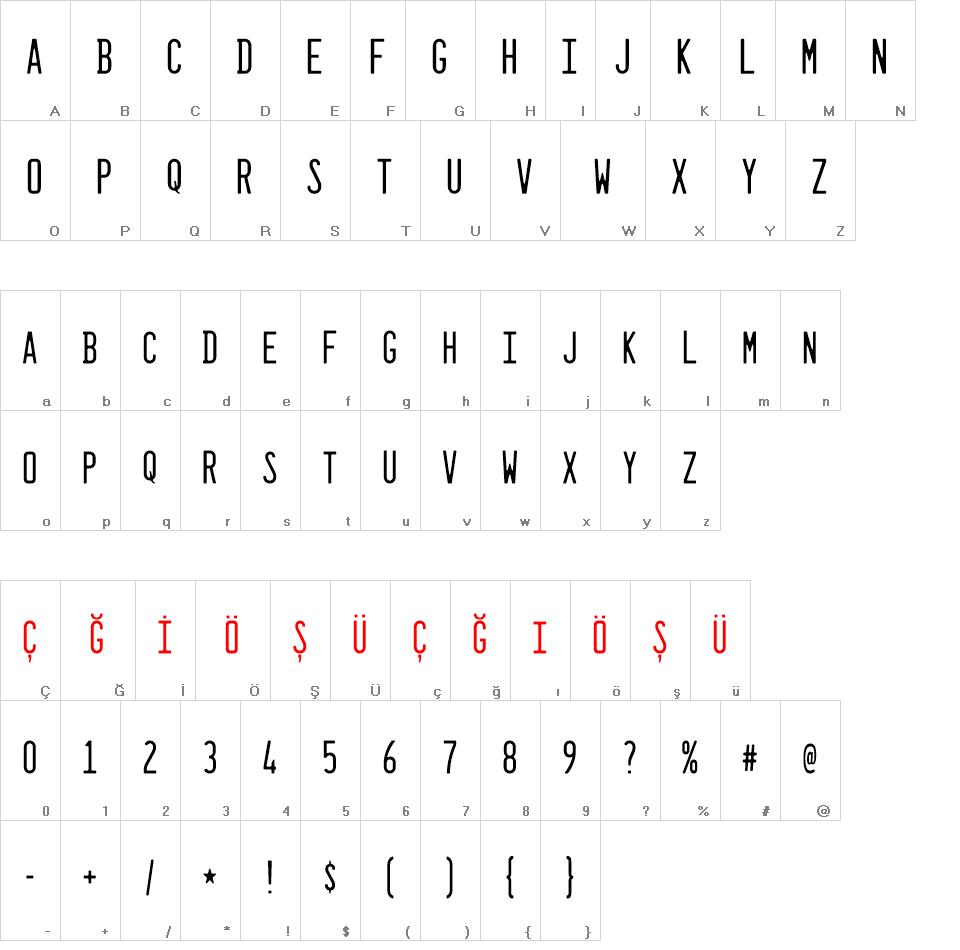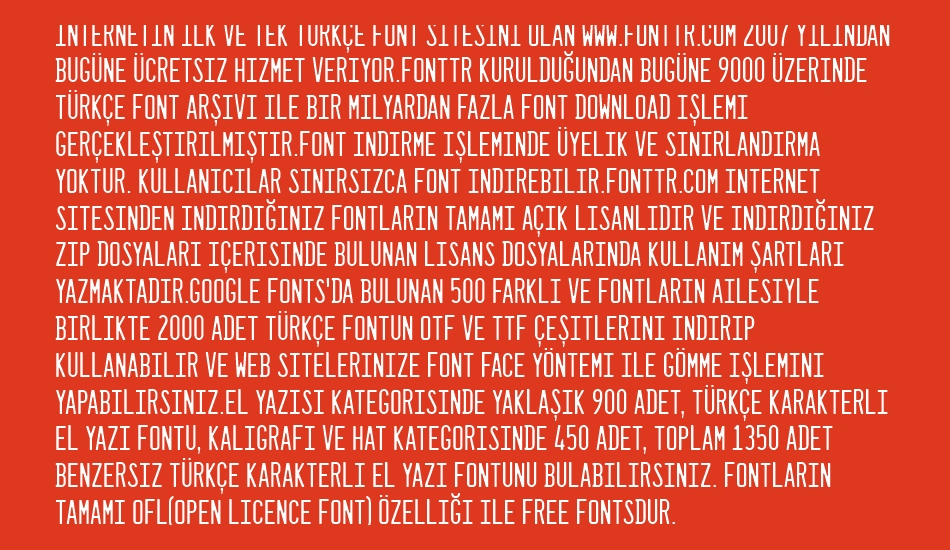
Dealerplate California font
Dealerplate, Amerika Birleşik Devletleri ve Kanada'daki çeşitli kabartma plakalara dayanan bir dizi 17 yazı tipidir. Dealerplate yazı tiplerinin çoğu, 2019 itibariyle en yeni kabartma stiline sahiptir. Daha otantik, monospaced bir görünüm elde etmek için harfleri kapatmayı deneyin. Vietnamca, Kiril dilleri ve Yunanca dahil olmak üzere hemen hemen tüm Latin kökenli dilleri desteklemektedir. Dealerplate California'nın ticari kullanım masaüstü lisansı ücretsizdir.